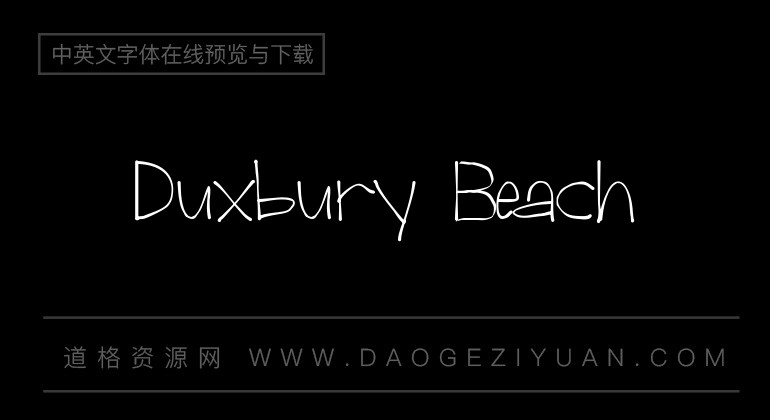
Duxbury Beach字体是一款由Font Diner推出的自由式字体。它拥有一种非常粗犷的外观,具有海滩风格的字体,可以用于标题,标签,广告,海报等设计。它有三种不同的字重,即正常,粗体和斜体,每种字重都有大量的字形,可以满足您的不同需求。此外,它还支持多种语言,可以支持多种文字格式。内容介绍
Duxbury Beach是一款非常不错的手写艺术字体,具有很好的视觉感,适合于文化类的宣传设计、商业类品牌的广告和产品包装设计以及个性化文字排版等较多场景。